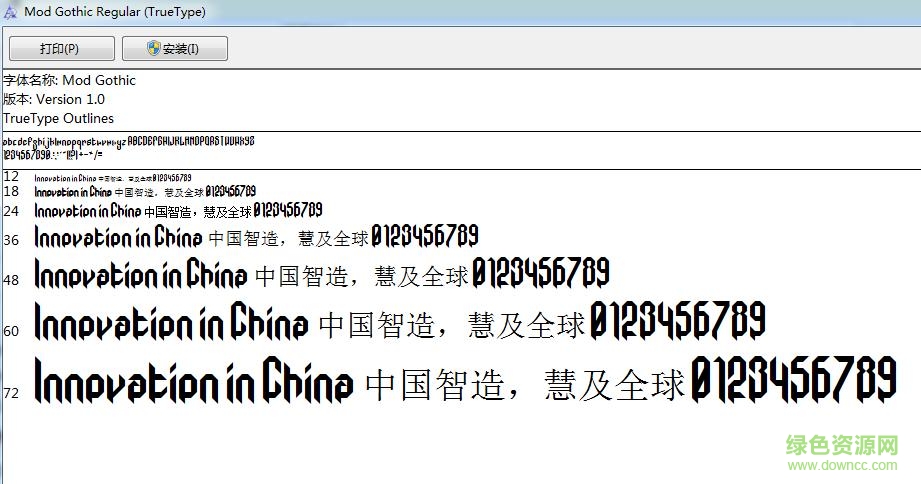
mod gothic字體是一款帶有神秘氣息大熱哥特式字體,字體結構復雜、字型設計充滿創(chuàng)意,華麗而典雅,常常用于網(wǎng)頁裝飾設計或是影視海報設計,需要的朋友歡迎免費下載!
1.跳躍明快,
2.深沉厚重,
3.簡潔爽朗,
4.飽含古韻,
5.格調(diào)高雅,
6.新穎獨特,
7.莊嚴雄偉,
8.華麗高貴,
9.個性非常突出!